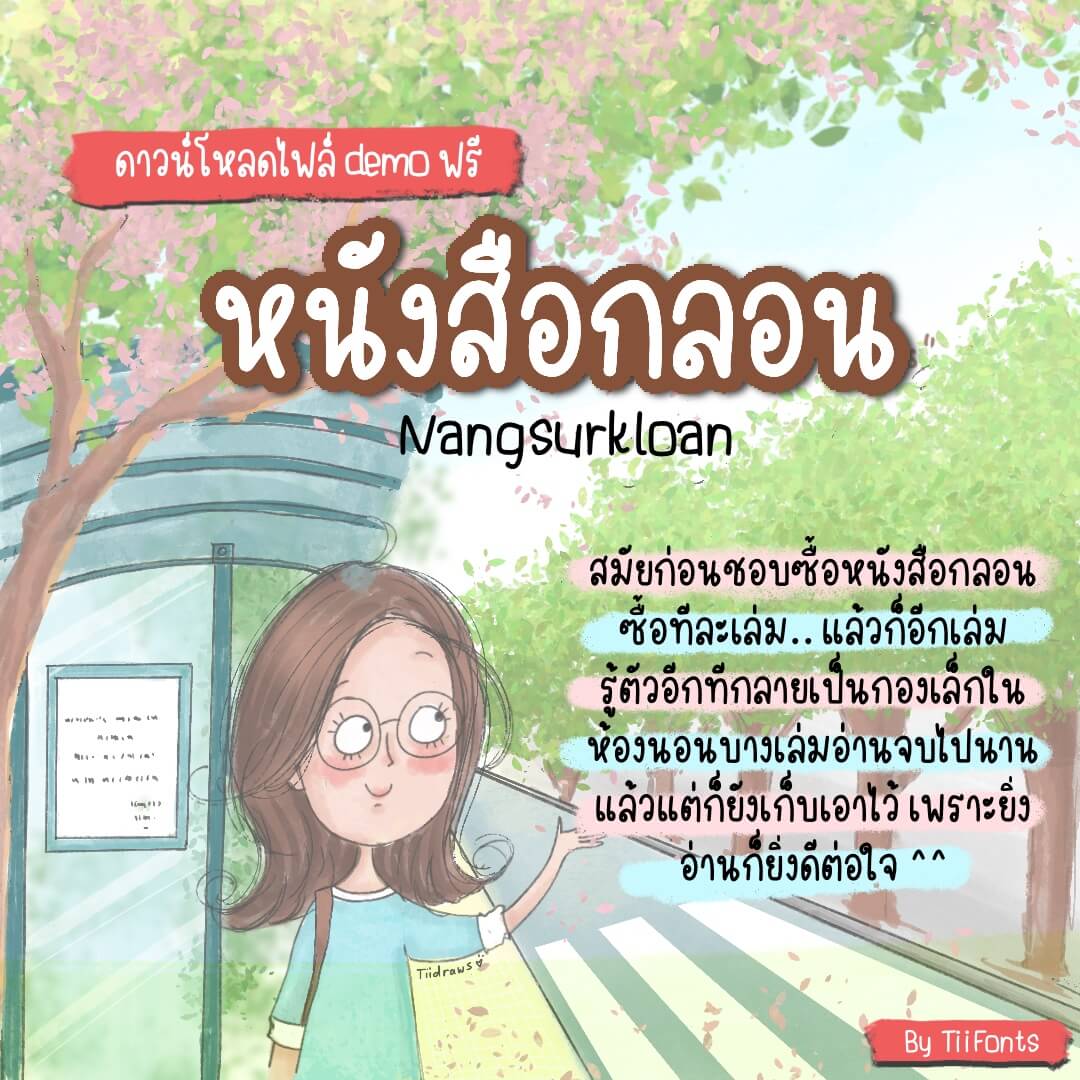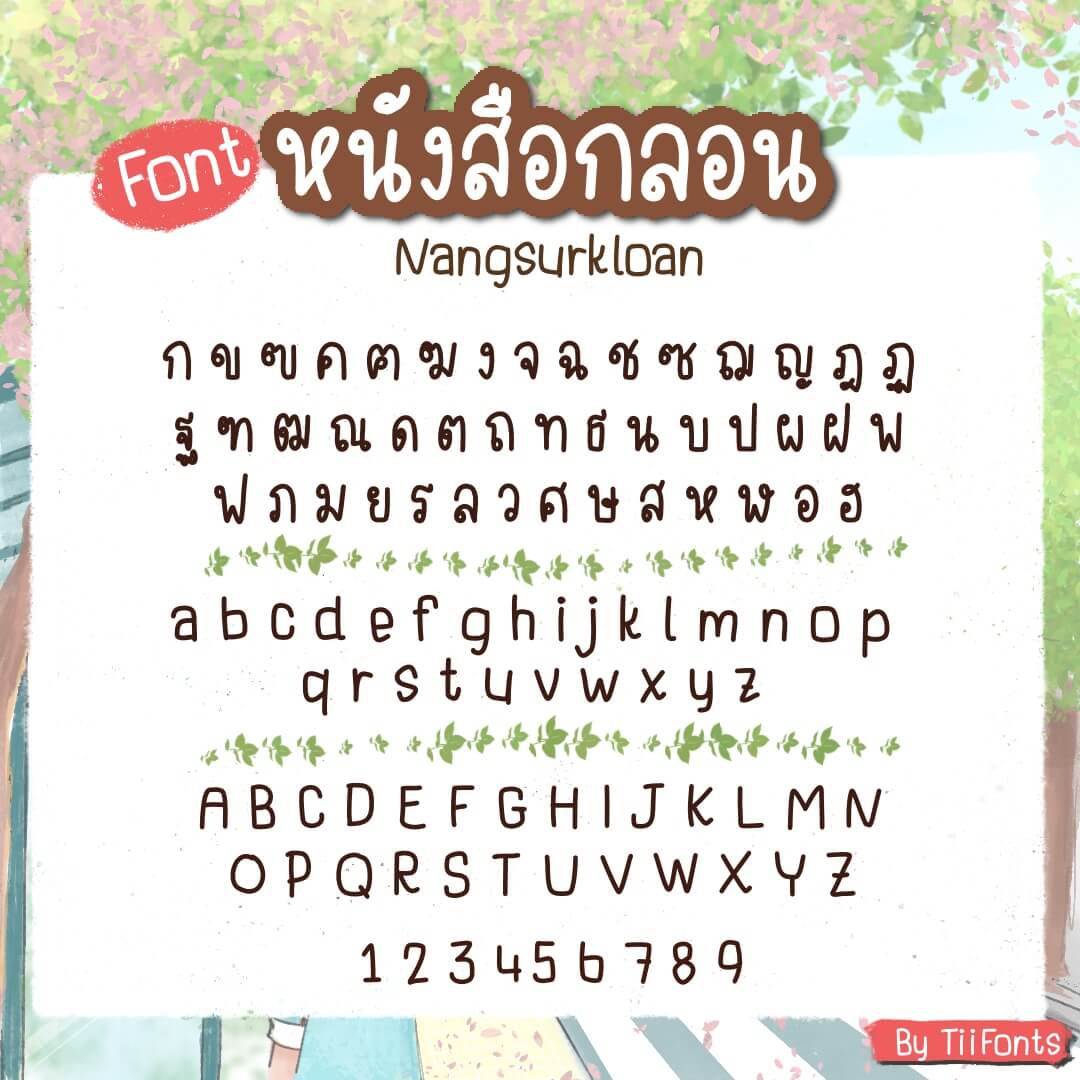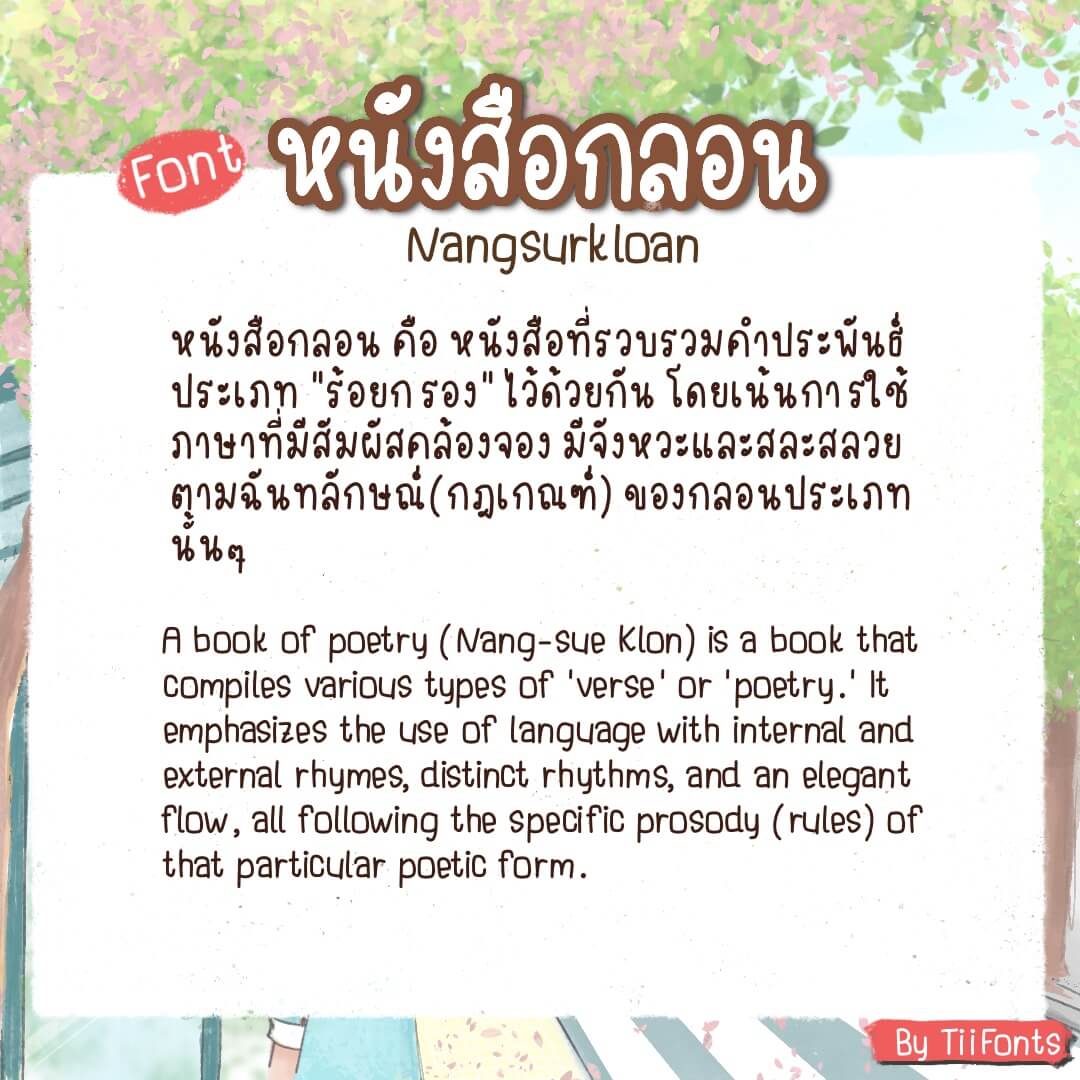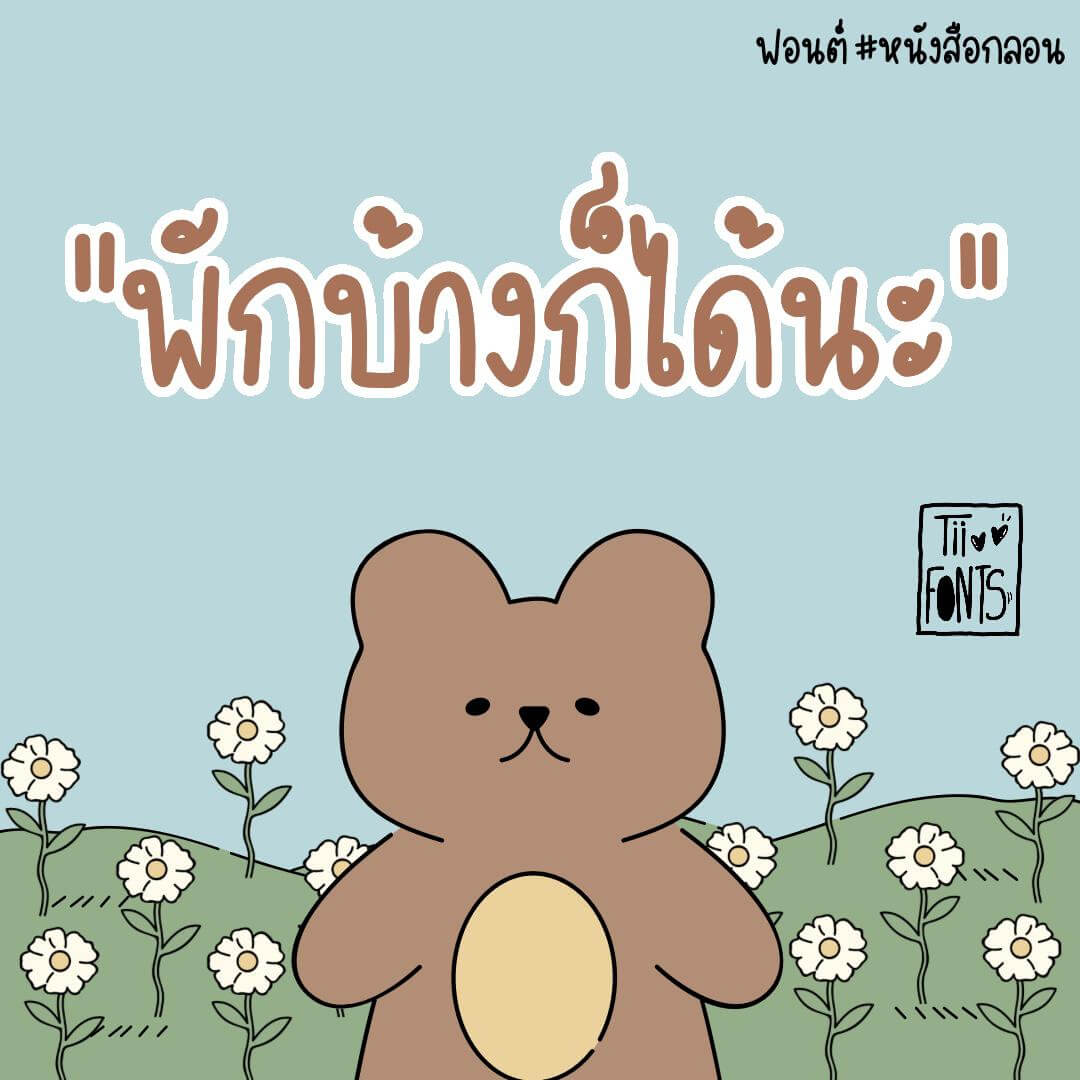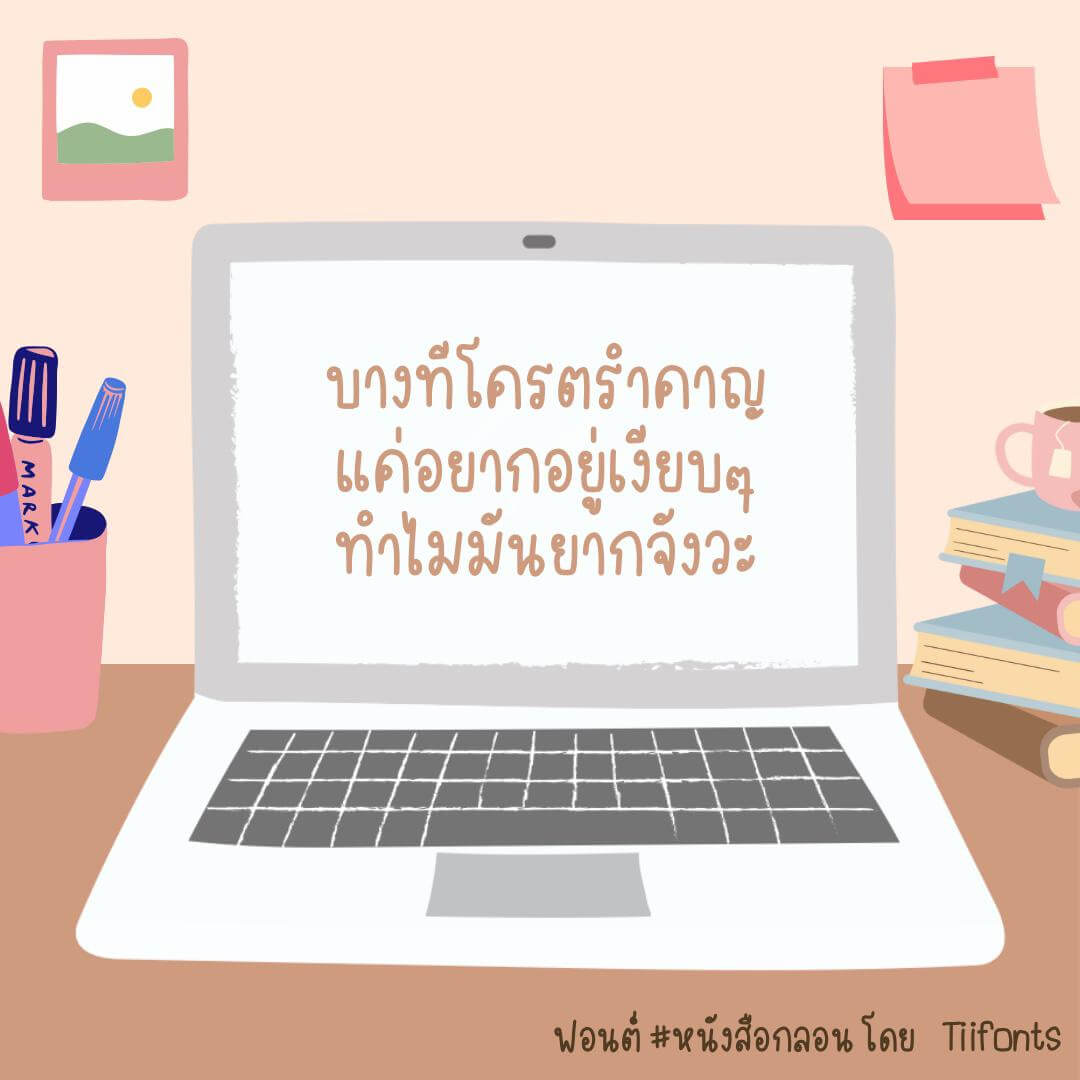
หนังสือกลอน (TTANangSurKloan)
ฟอนต์ลายเส้นน่ารัก อ่านง่าย มินิมัลหวานๆ ใช้งานง่าย จะจดสรุป ทำรายงานส่งอาจารย์ ตั้งเป็นฟอนต์มือถือ หรือใช้แต่งรูปก็ปัง
ที่มาที่ไป: สมัยเด็ก ไม่ทำอะไรเลยค่ะ จำได้ว่าสิ่งเดียวที่ชอบทำคือการอ่านหนังสือ ชีวิตวนๆ อยู่กับบ้านและร้านหนังสือในห้าง ช่วง ม.ปลายถึงมหาลัยปีหนึ่ง เริ่มชอบอ่านหนังสือกลอน ความน่ารักของหนังสือ ความสละสลวยหวานเจี๊ยบของภาษา และที่หลงรักสุดๆ คือลายมือสวยๆ ที่เห็นได้ในหนังสือกลอนหลายๆ เล่ม
มันเป็นแรงบันดาลใจให้เราเริ่มฝึกลายมือและฝึกแต่งกลอนไปพร้อมๆ กันจนได้ลงตีพิมพ์ได้มีหลังสือกลอนเป็นของตัวเองกับสำนักพิมพ์หนังสือกลอนแห่งหนึ่ง (ต้องนั่งคัดกลอนลงกระดาษ A4 บทละแผ่นรวมทั้งหมดประมาณ 60 กว่าบท แล้วใส่ซองส่ง สนพ. ทางไปรณีย์ กว่าจะได้ตีพิมพ์ก็แก้นู่นนี่ ส่งต้นฉบับไปๆ มาๆ อยู่หลายรอบเลย)
และนั่นเป็นที่มา 80% ของฟอนต์ตัวนี้เลยค่ะ มันมาจากความคิดถึงชีวิตสมัยก่อนที่ไม่มีอะไรมาก ไร้อินเทอร์เน็ต ไร้ AI วันๆ หาความสุขได้จากเพลงในตลับคาสเซ็ตกับหนังสือกลอน ^^